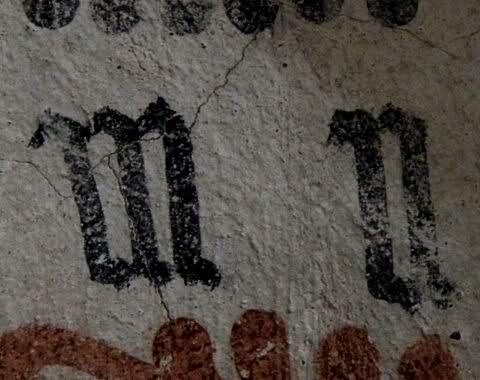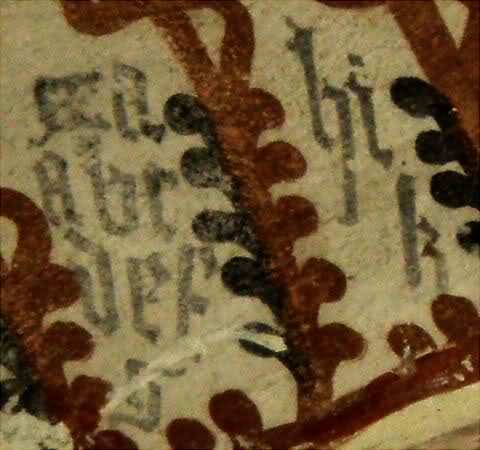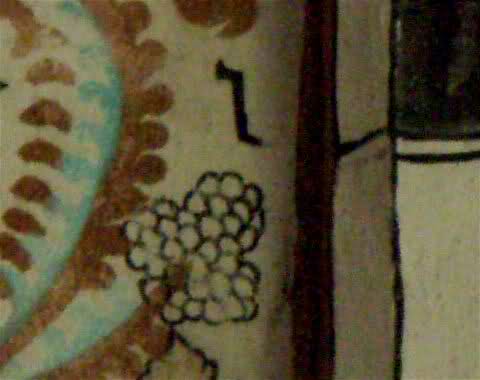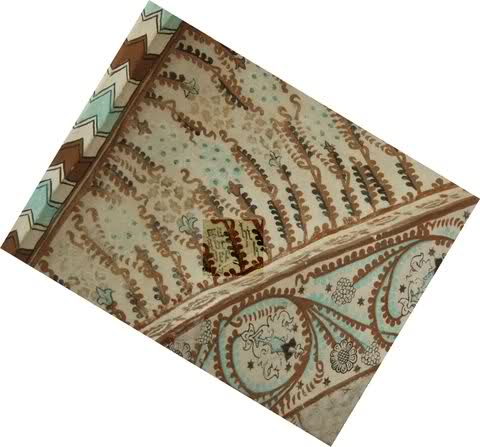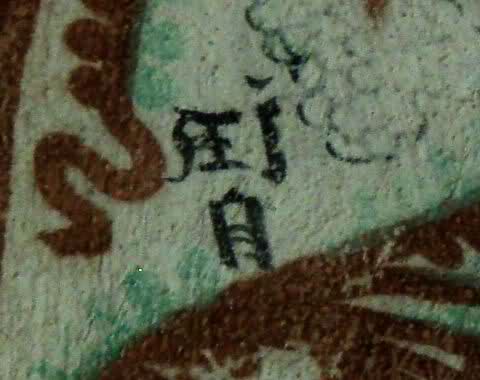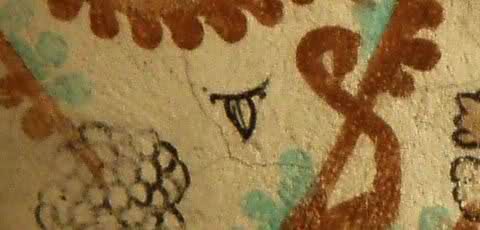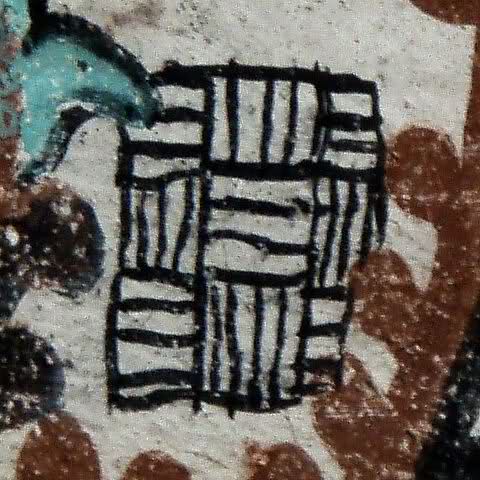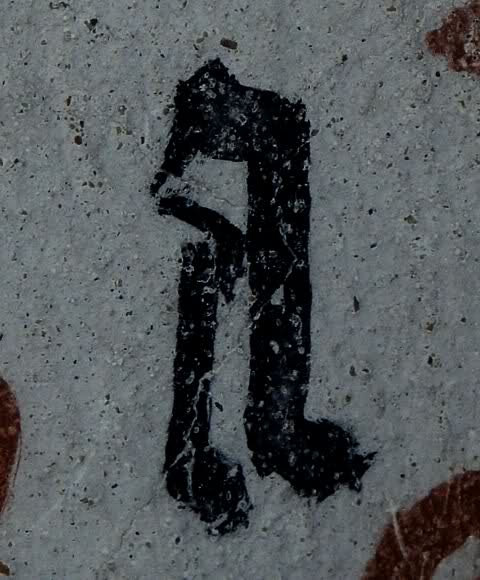
Kalkmalerei mit gotischen Schriftzeichen (Hilfe gesucht)
… wehrend ich noch darueber ueberlegte, warum Wissenschaftsmänner festgelegt hatten, dass der Text in der Kalkmalerei im Deckengewölbe unserer alten Kirche „Ytterlännäs“, „ Maalede Eghil“ heissen soll.
(Malerei ca. 14. Jahrhundert.)
Denn ich erkenne nur die Anfangsbuchstaben des Alphabets. Entdeckte ich im Muster der Deckenmalerei ein Schriftzeichen nach dem Anderen. Auch die Deutung des Alphabets fand seine Bestätigung an anderer Stelle wieder. Selbst in vergleichbaren Kirchenkalkmalereien ist mir diese sonderbare Darstellung von Schriftzeichen nie aufgefallen.
Was haben diese „gotischen“ Schriftzeichen fuer eine Bewandtnis, welche Bedeutung? Gibt es ähnliche Darstellungen? Initialen oder Zunftzeichen möchte ich einmal ausschliessen.
Wer kann Auskunft geben, wer kann helfen?
Meines Erachtens haben diese Schriftzeichen keinen tieferen Sinn und auch keine Bedeutung. Der Maler hat diese Buchstaben als Ornament verwendet. Man sieht an den ungelenk geformten Buchstaben, dass hier jemand am Werk war, dem der Bauplan, welcher der Buchstabenform zugrunde liegt, nicht bekannt war. Er hat Buchstabe für Buchstabe nach einer Vorlage zu kopieren versucht und war sichtlich von der Schrift fasziniert, deren Bedeutung er wahrscheinlich noch nicht kannte. So sah er Schrift als Bild bzw. Ornament.
... dafür erscheint aber die Platzierung im Gesamtornament zu beliebig zu sein.
Mich würde interessieren, ob diese Zeichen ein Einzelfall sind - vielleicht gibt's ja in der Region noch weitere Kalkmalereien aus der gleichen Zeit? Und hätten die dann auch Buchstaben?
Gerade die wahllose Anordnung der Buchstaben spricht dafür, dass hier kein tieferer Sinn dahinter liegt. Der ganzen Schriftanordnung liegt offensichtlich ein auch in der Kunstgeschichte öfters erwähnter „horror vacui“ zugrunde.
Es handelt sich hiebei um die oft zu beobachtende Neigung des Menschen, leere Flächen mit Bild oder Text zu füllen. In diesem Fall wurden die Leerflächen zwischen den Ornamenten mit Buchstaben gefüllt.
Heute finden wir das in der Graffiti-Kunst.
Die Schriftzeichen sind wahllos angeordnet, sie ergeben kein Muster. Soweit uns bisher bekannt ist sind in noch vergleichbar, verbliebenen Kalkmalereien keine derartige Zeichen vorhanden. Leider sind ebenfalls in Kirchen´s schwarzer Zeit die Seitenwände weiss uebermalt wurden. Viele dieser kleinen Kirchen hat man in Schweden zu Beginn des 18. Jahrhunderts abgerissen und durch neue „08/15“ Kirchenbauten ersetzt.
Merkwuerdig bleiben dennoch die beiden Schriftzeichengruppen mit den Alphabetanfängen bis zum „k“. Warum stehen am Anfang drei „A“ in verschiedenen Schriftstielen?
Gotische „Graffiti“, dass währe ja entsetzlich, ich glaube, ich sollte die Nachforschungen doch lieber ruhen lassen. :oops::lol: